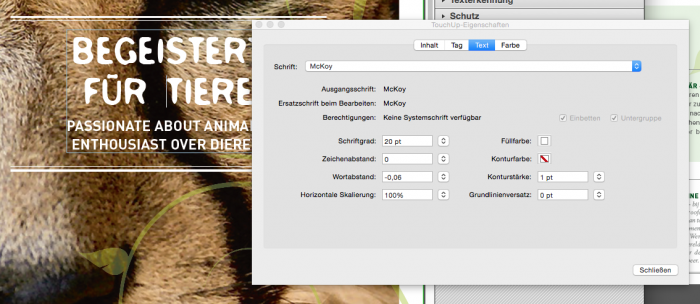
Plakatschrift Kölner Zoo gesucht!
Suche die Schrift die auf fast allen Plakaten des Kölner Zoo verwendet wird.
Diese stammen aus der Feder der Agentur Preuss und Preuss.
Zu sehen hier:
oder hier:
Die Suchen über WhatTheFont oder identifont sowie bei MyFonts und Anderen selber brachten keine Ergebnisse.
In ihren pdfs verwenden sie die McKoy.
Das ist ja fast ein Grund mit Blur, Holstein, McKoy und ähnlichen Vektorisierungs-Unfall-zum-Prinzip-erhoben-Schriften eine neue Schriftenliste zu starten
ja, ich dachte, die zeiten der blur(-klone) seien vor ungefähr zehn, fünfzehn jahren vorbei gewesen. mir ging es beim sehen der plakate also ungefähr so wie der frau hier links oben ;-)